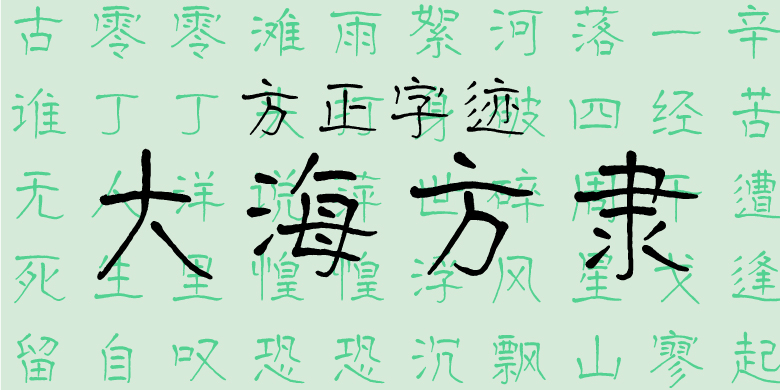
方正字迹-大海方隶
字体品牌: 方正字迹 设计师:姚海通 字体分类:常规书写·硬笔 字体属性:精品字 字符集:大陆简体(GB2312-80)、简繁扩展(GBK) 发布时间: 2023
该字体汲取《乙瑛碑》的方正严谨的结构,融合《石门颂》书写上的宽松率真的特点,并将字体重心稍微上移,结构险中求稳,笔画形状多呈圆头细脚,若行云流水,潇洒自如。